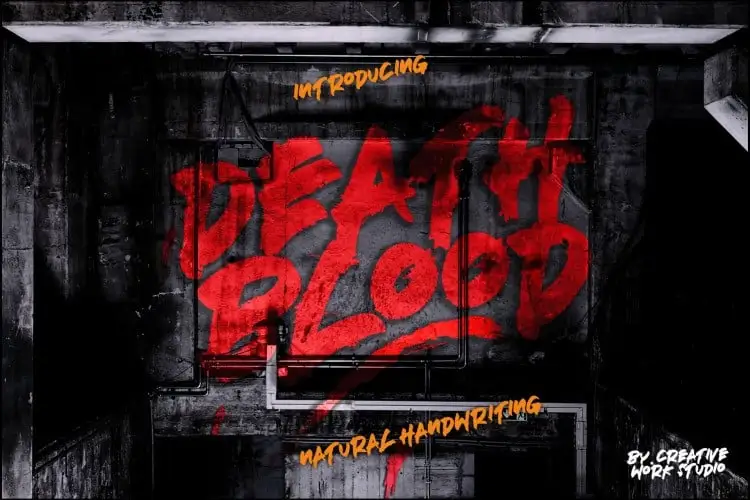
Deathblood Brush Font – Download Grátis
A Deathblood Brush Font é uma elegante e única fonte script que captura a essência de um estilo natural e autêntico. Originada do designer creativework69, essa fonte sans serif foi criada à mão com um toque robusto e compacto, repleta de imperfeições característicos das tintas esfumadas, dando-lhe uma aparência realista e quase natural. Com textura rude que melhoram ainda mais a escrita manual, esta fonte é perfeitamente adequada para estilos vibrantes, emoção e mistério, ideais para títulos de filmes, capas de livros, rótulos de produtos ou nomes de marca. É um recurso visual único e interessante para designers e criativos em busca de algo que se destaque no design gráfico.